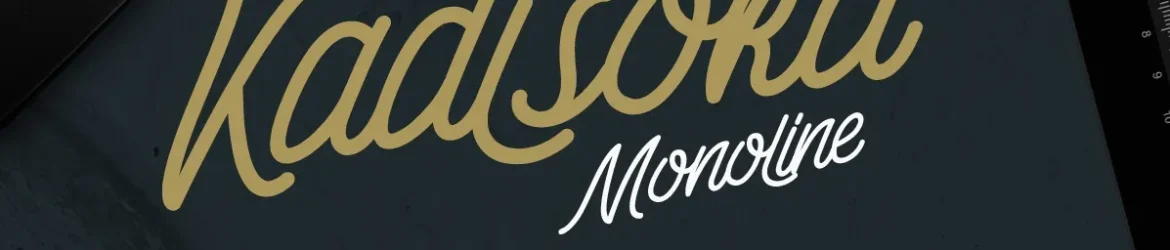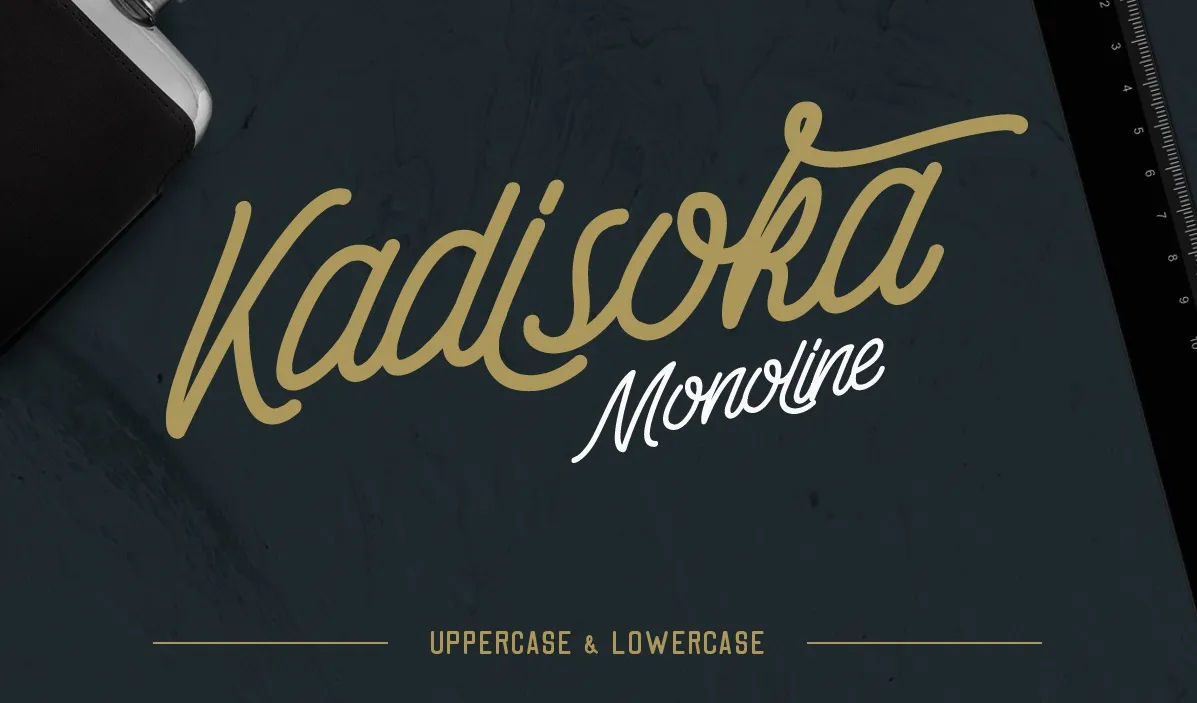
Kadisoka Monoline Font
Descubra a Kadisoka Monoline Font, uma elegante escolha para personalizar textos. Criada pelo designer Hamilton, esta fonte é perfeita tanto para uso pessoal quanto comercial sem custos adicionais. Mas não se contentando apenas com isso, oferecemos um verdadeiro upgrade de experiência ao disponibilizar sua versão completa em breve. Esta versão gratuita vem equipada com uma ampla gama de caracteres, enquanto a versão completa tem ainda mais opções e inclui três fontes adicionais além de modelos de logotipos. Uma vez que você tenha adquirido a versão completa da Kadisoka Monoline Font, pode explorar seu poderoso conjunto de recursos. A versão gratuita permite um visualizador rico em detalhes, mas com a possibilidade de desenvolver suas próprias criações de logotipos e designs únicos. Não se preocupe, ainda há muito mais para descobrir na versão completa. É uma fonte perfeita tanto para designers profissionais quanto para amantes da arte, já que oferece um design único e harmonioso. Estamos animados em apoiar nossos designers com esse inovador recurso de design.